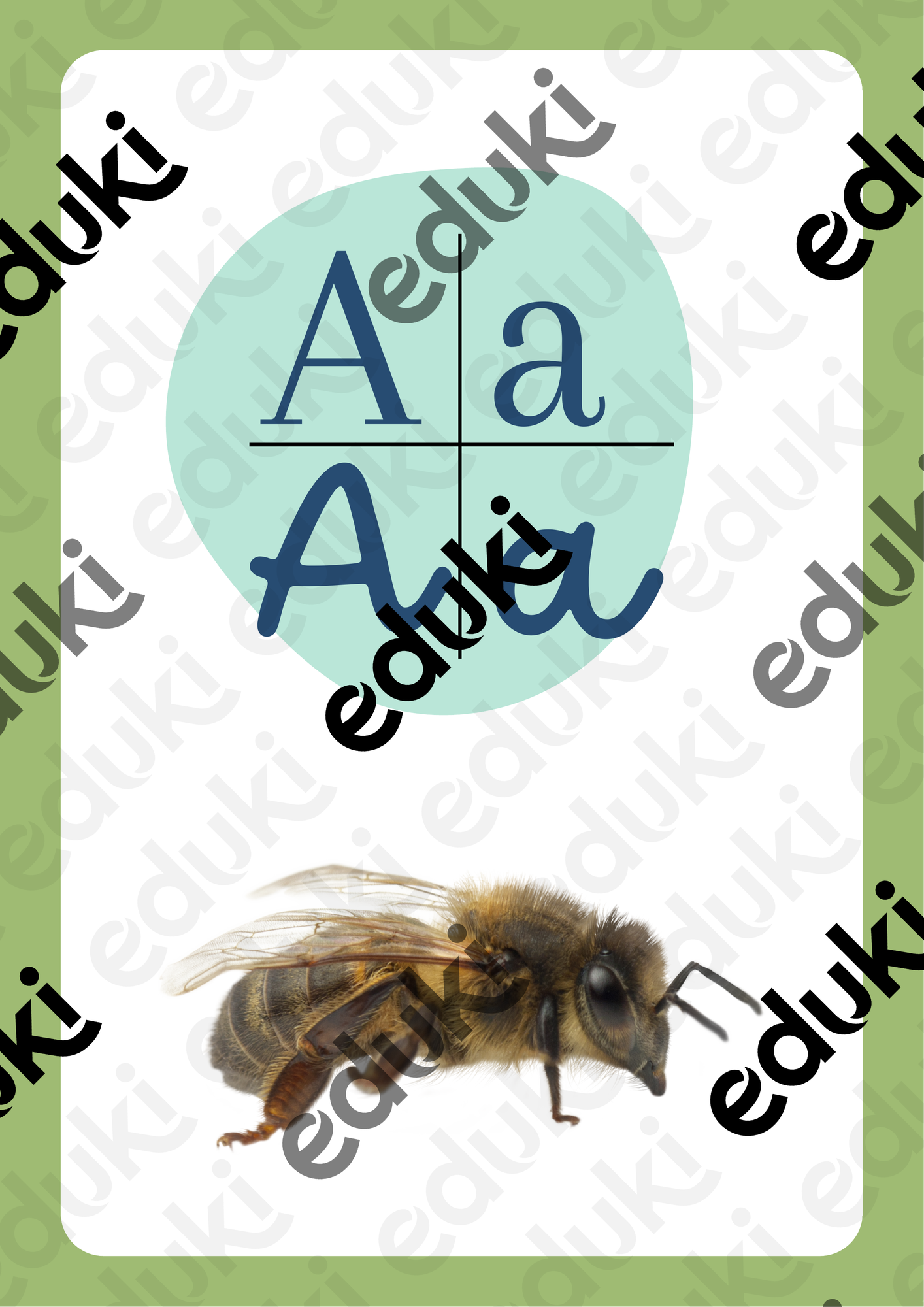
PDF imprimible de carteles del abecedario en color, diseñado 4 tipo de tipografías distintas llamativas, acompañado de ilustraciones atractivas que representan cada letra. Perfectos para aulas decorar, rincones de lectura o habitaciones infantiles, fomentando el aprendizaje del abecedario de manera visual y creativa.
ABC 4tipografias - imagen real